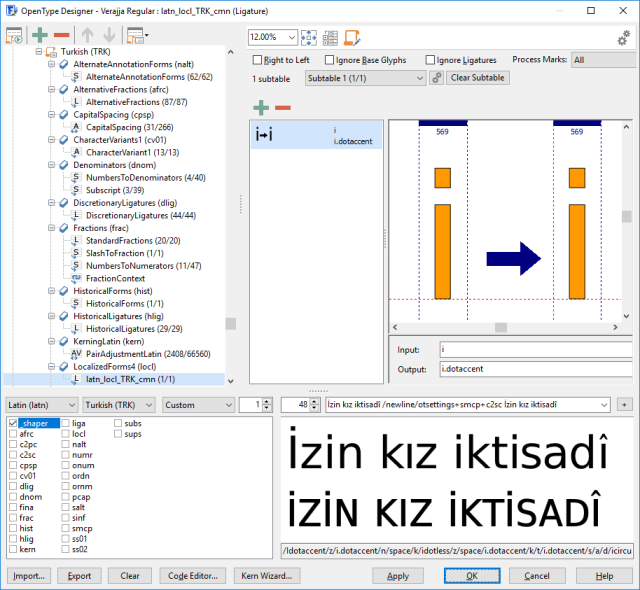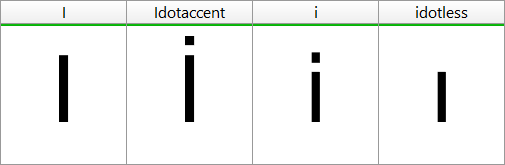
如果您的字型覆蓋土耳其語支援,並且包含 OpenType 特性,請務必為土耳其文 i 新增本地化字形。
如果您的字型支援土耳其語,並且還包含使用帶點的 i 和無點的 i 的 OpenType 功能,如小型大寫字母和小型大寫字母,請務必為土耳其語 i 新增本地化形式,因為土耳其語字母有一些不尋常的地方。像許多其他語言一樣,它基於拉丁指令碼,但不是 2 種型別的 i,即帶點的小寫 i 和無點的大寫 I,而是包含 4 種型別。這會產生一個問題,因為預設的大小寫規則不再適用。如果您將 i 大寫,它會變成 I,但對於土耳其語文字則不然,因為那時 i 會變成 İ,而 ı 會變成 I。
常規的小型大寫字母和小型大寫字母功能不考慮這些規則,會將常規小寫 i 更改為無點的大寫 I,因此對土耳其語失敗。在這種情況下,可以使用本地化形式來修復此語言特定問題。
您可以使用 FontCreator 輕鬆地向字型新增本地化形式功能。首先確保您有一個名為 i.dotaccent 的額外字形,它是常規 i 的副本。如果您使用了名為 Unmapped Latin Small Capitals 的轉換指令碼,您的字型已經包含此字形。如果沒有,請執行字形轉換指令碼,或透過插入字形對話方塊手動新增缺失的字形。在按名稱文字區域中提供此字形公式:
i.dotaccent=i
如果您的字型也包含小型大寫字母,請也新增該變體。
接下來,轉到 OpenType 設計器並單擊左上角的工具欄項。確保選中常用本地化形式選項以及您想要的其他功能,如小型大寫字母和小型大寫字母,然後單擊確定按鈕以生成 OpenType 佈局功能。
OpenType 功能和查詢現在已新增到您的字型中,如上所示。由於還有更多語言(亞塞拜然語、克里米亞韃靼語、哈薩克語和韃靼語)也存在相同問題,它們也包括相同的修復,因此不必擔心。
您可以輸入預覽文字來測試您的功能。您可以輸入字母或斜槓後跟字母的字形名稱。您甚至可以新增換行符並覆蓋 OpenType 佈局功能設定,就像我們為了顯示常規文字和小型大寫字母之間的區別所做的那樣。
İzin kız iktisadî /newline/otsettings+smcp+c2sc İzin kız iktisadî
請注意,土耳其語也支援 i 揚抑符,如今很少使用,不會引起問題,因為 î 的大寫是 Î,就像其他基於拉丁語的語言一樣。